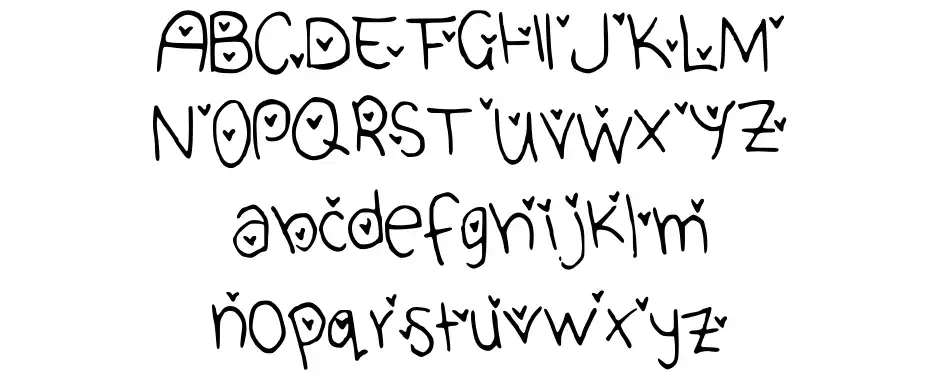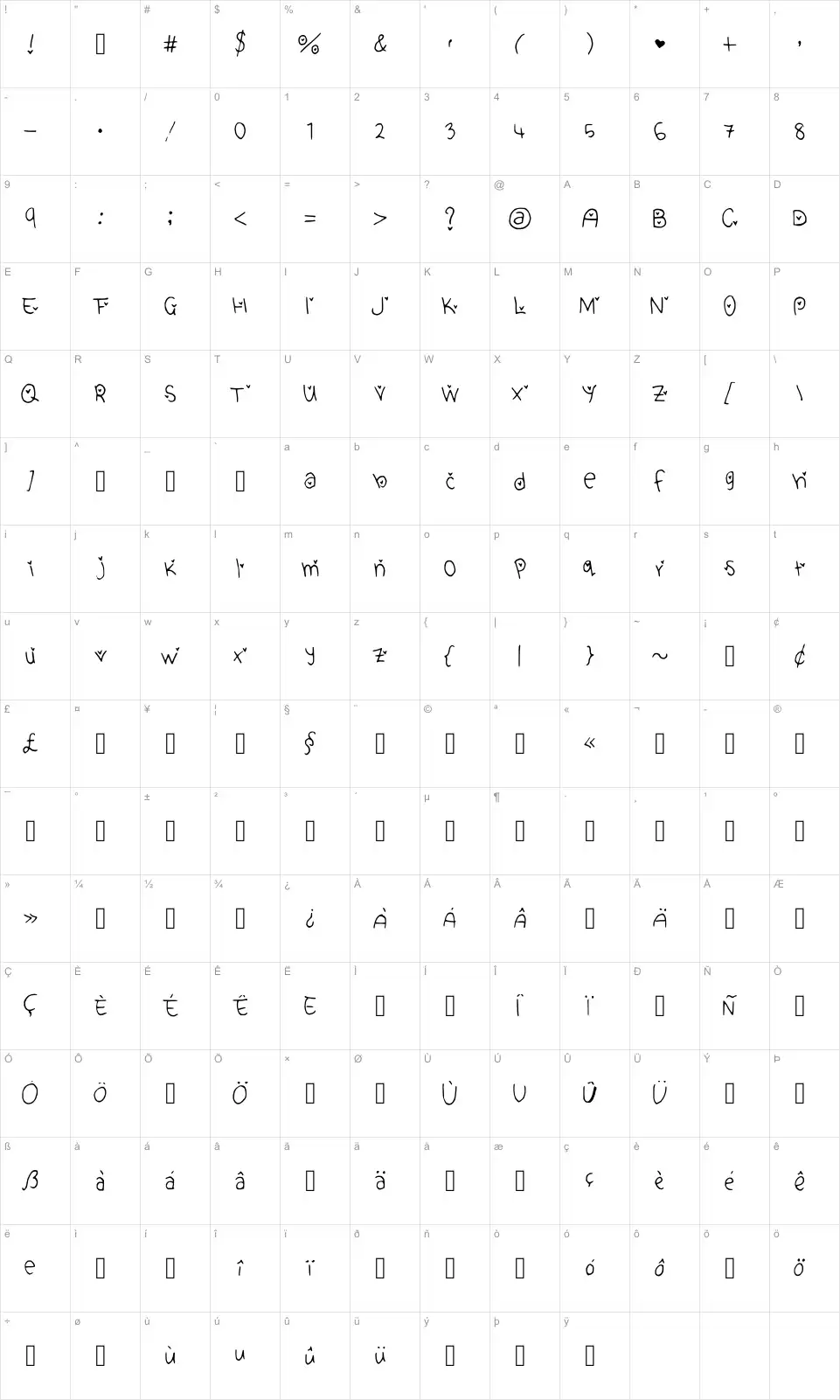
Cute Heart Font – Download Grátis
A fonte ‘Cute Heart Font’, criada por Paula Tennet, é perfeita para qualquer projeto natalino ou para o Dia dos Namorados. Se você está procurando por esta fonte, não perca a oportunidade de baixá-la ou gerar uma pré-visualização personalizada de texto para ver como ela ficará antes de usá-la. Esta fonte, com uma licença gratuita, é disponível em formato TTF e pode ser usada para adicionar um toque delicado e amoroso a seus trabalhos, especialmente nos feriados de Natal ou Dia dos Namorados. Adicionada em 12 de julho de 2022, a ‘Cute Heart Font’ já foi descarregada 8198 vezes e tem um tamanho de arquivo de 22 KB. Ela pertence à categoria de Dia de Natal, tornando-a uma opção perfeita para o seu próximo projeto natalino.